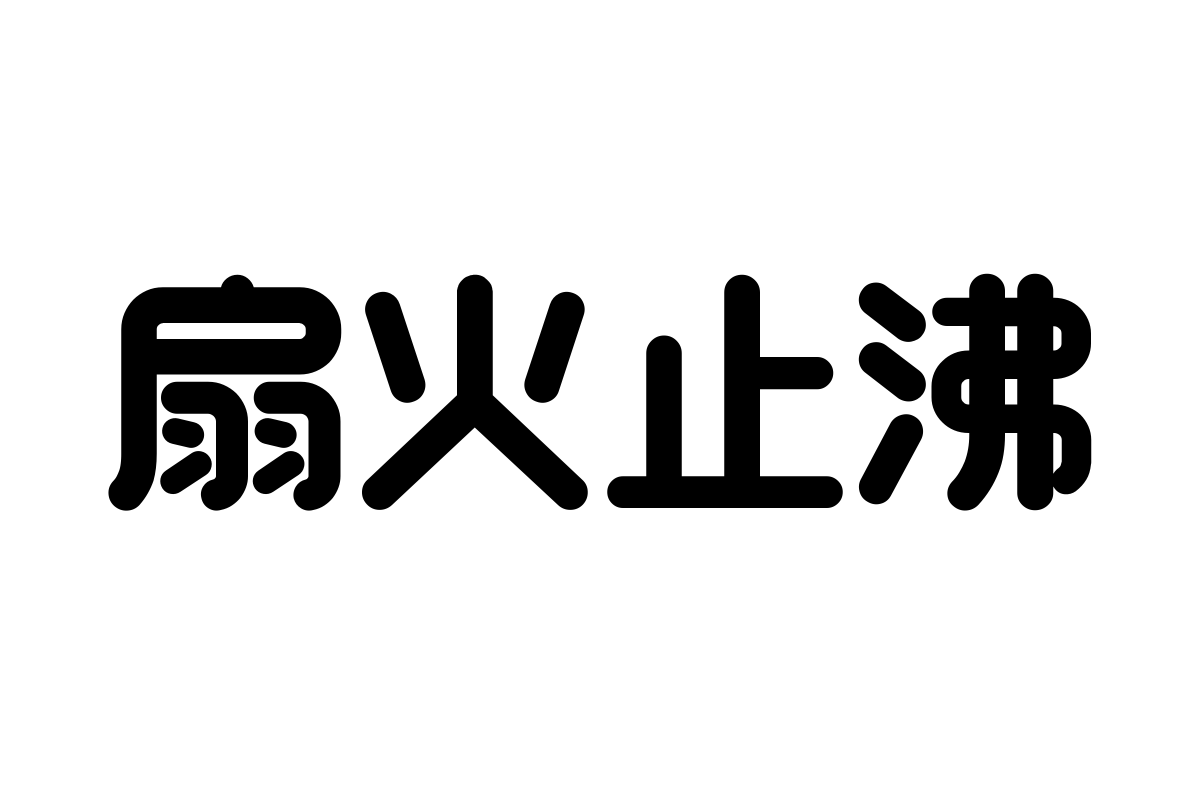
汉仪铸字稚圆 W 是一款由汉仪公司开发的中文字体,专为儿童和青少年设计。这款字体以其圆润、可爱的外观受到广泛欢迎,适用于儿童书籍、教育材料、广告宣传等场景。
汉仪铸字稚圆 W 的特点如下:
1. 字形圆润可爱:该字体采用圆润的线条和形状,给人一种温馨、亲切的感觉,适合儿童的审美需求。
2. 字体大小适中:汉仪铸字稚圆 W 支持多种字体大小,从小到大均可调整,方便设计师根据实际需求选择合适的字体大小。
3. 可变间距:该字体支持自定义间距,用户可以根据需要调整字体之间的间距,使文字更加协调美观。
4. 易于识别:汉仪铸字稚圆 W 采用了简洁明了的设计,使得文字更加易于识别,提高阅读体验。
5. 适用范围广泛:该字体适用于各种场合,如儿童图书、教育软件、广告宣传等,具有很高的实用价值。
总之,汉仪铸字稚圆 W 是一款专为儿童设计的中文字体,以其圆润可爱的外观深受喜爱。它适用于各种应用场景,具有较高的实用性和广泛的市场前景。